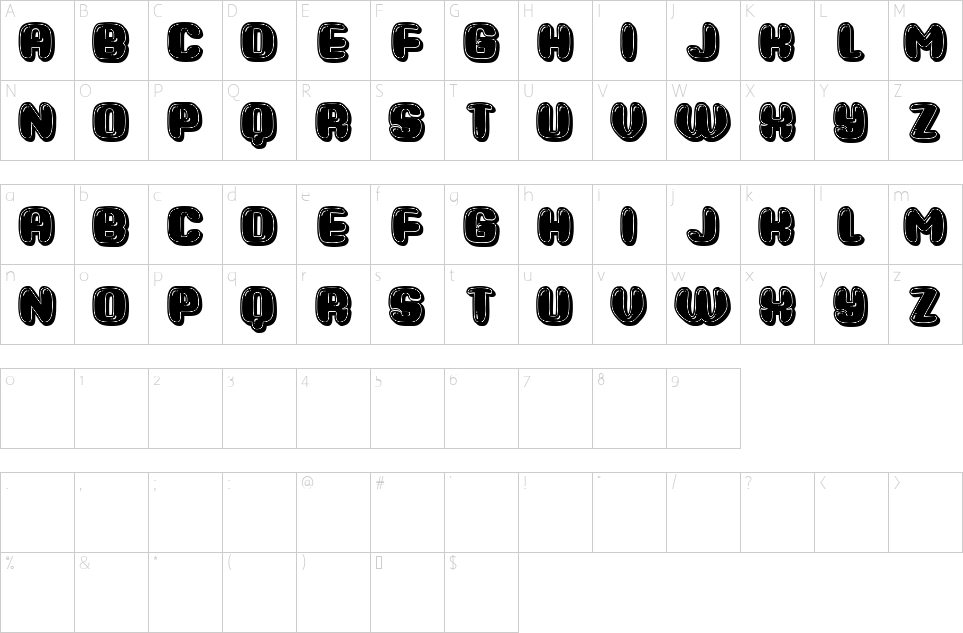
Descubra a nova Darixmaq Font para Windows e Mac, uma criação visionária do designer Vladimir Nikolic. Esta elegante e sofisticada fonte combina elementos modernos com um toque nostálgico, criando um visual único que se destaca em qualquer projeto digital. Seja você um profissional de design ou alguém que busca adicionar a sua marca pessoal, Darixmaq oferece uma experiência gráfica única e incrível. Com mais de 317 downloads, já é um sucesso entre os designers brasileiros buscando algo novo e sofisticado para seus projetos. Descubra por si mesmo o brilho da Darixmaq Font hoje.